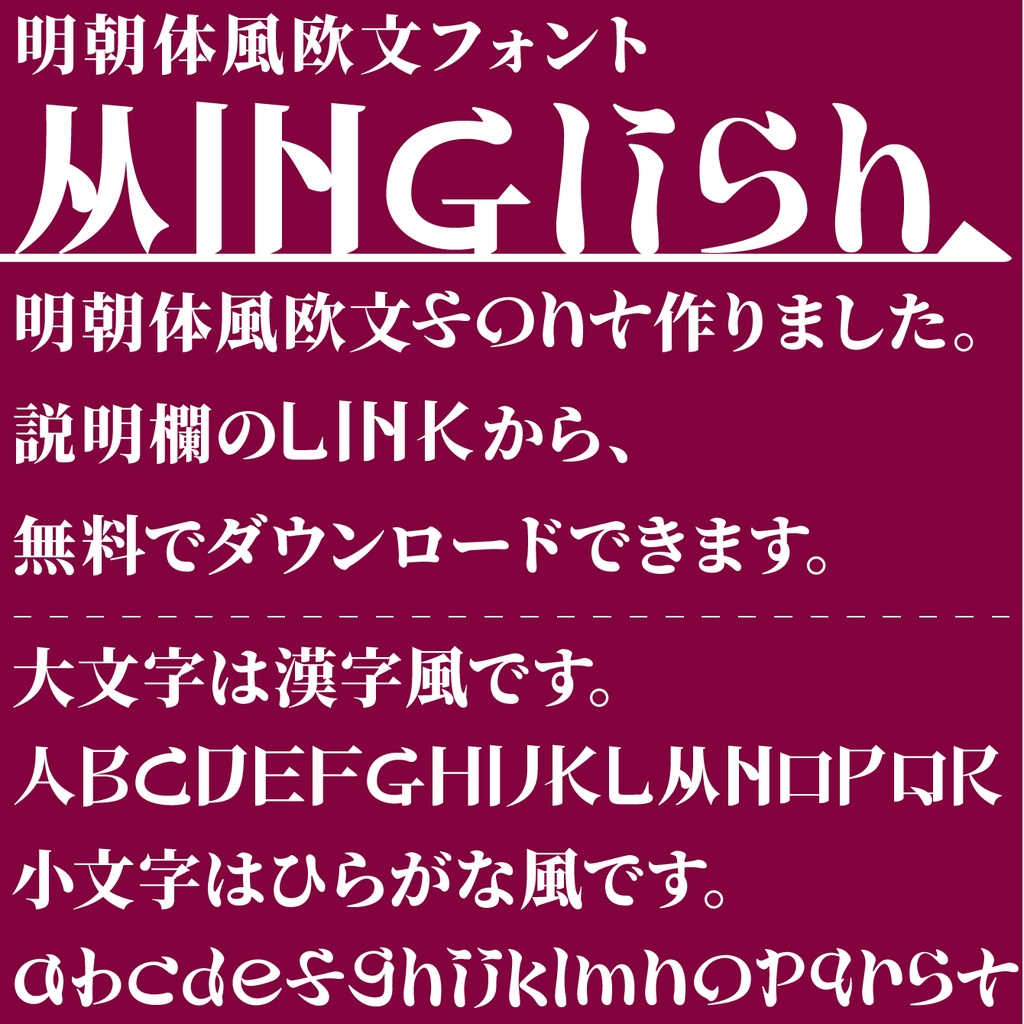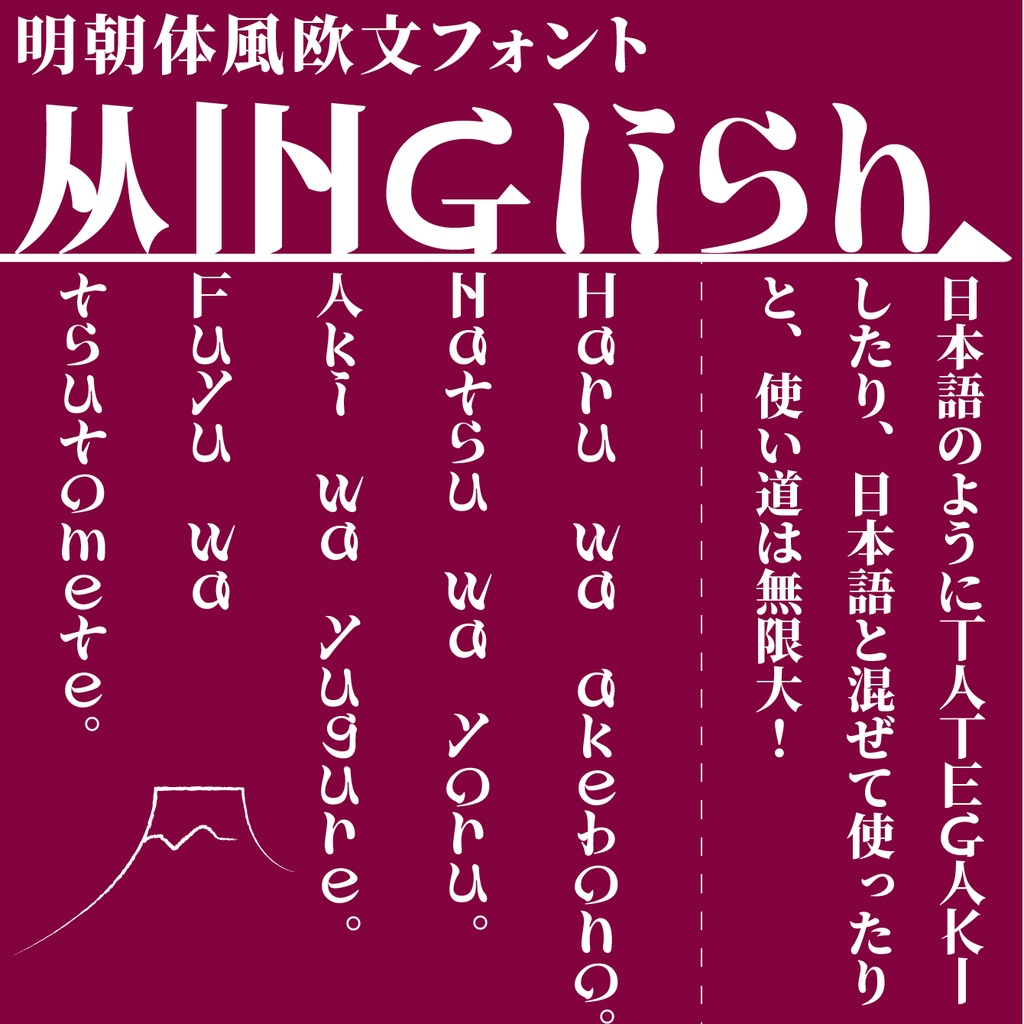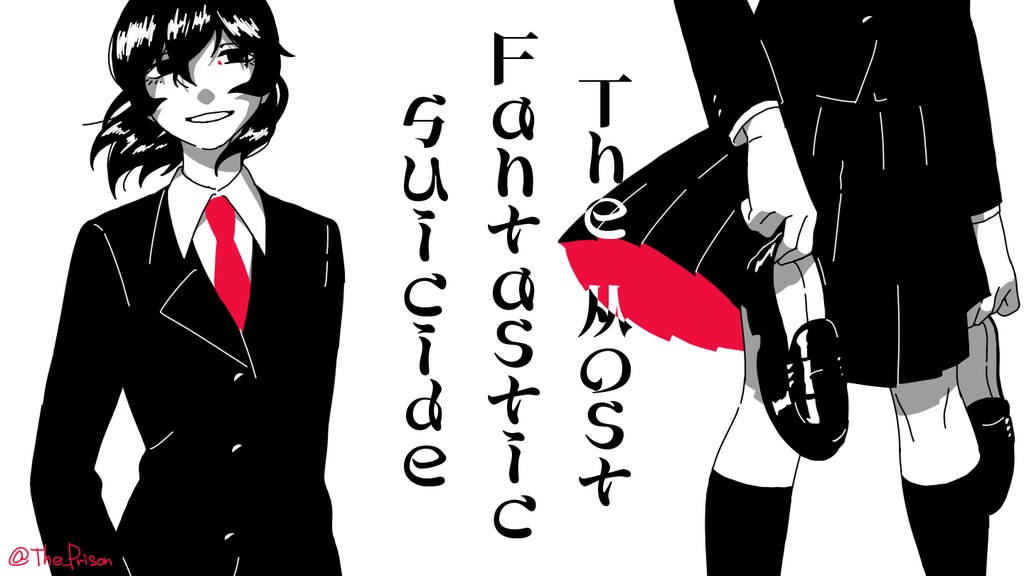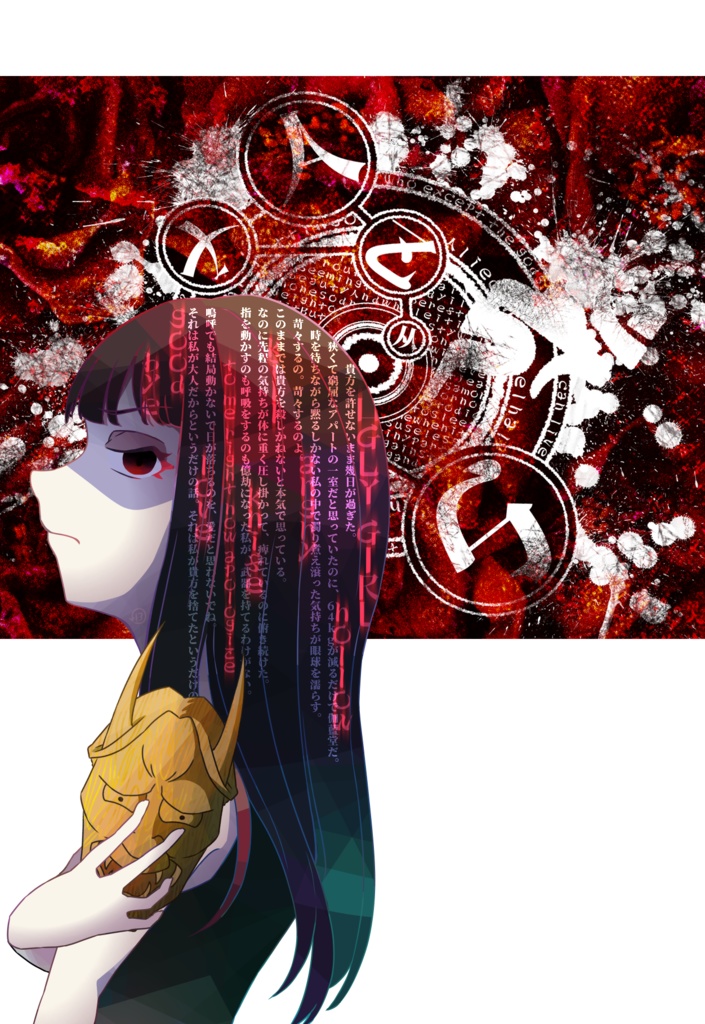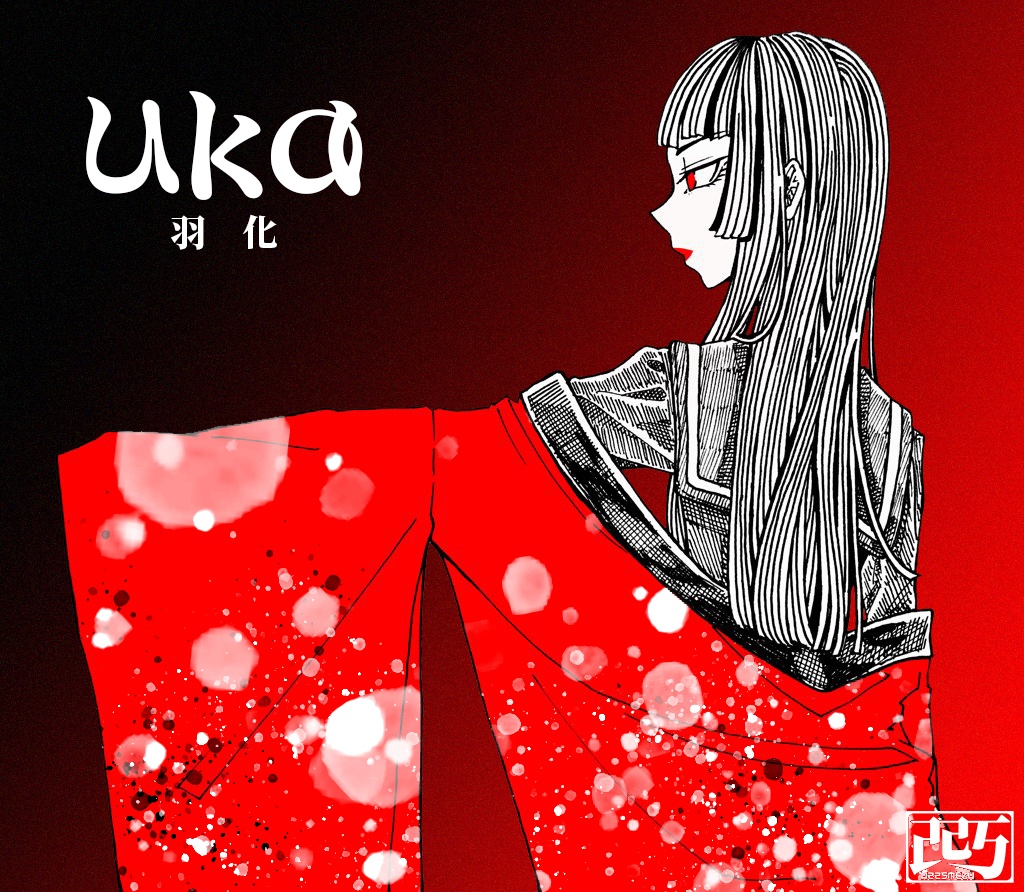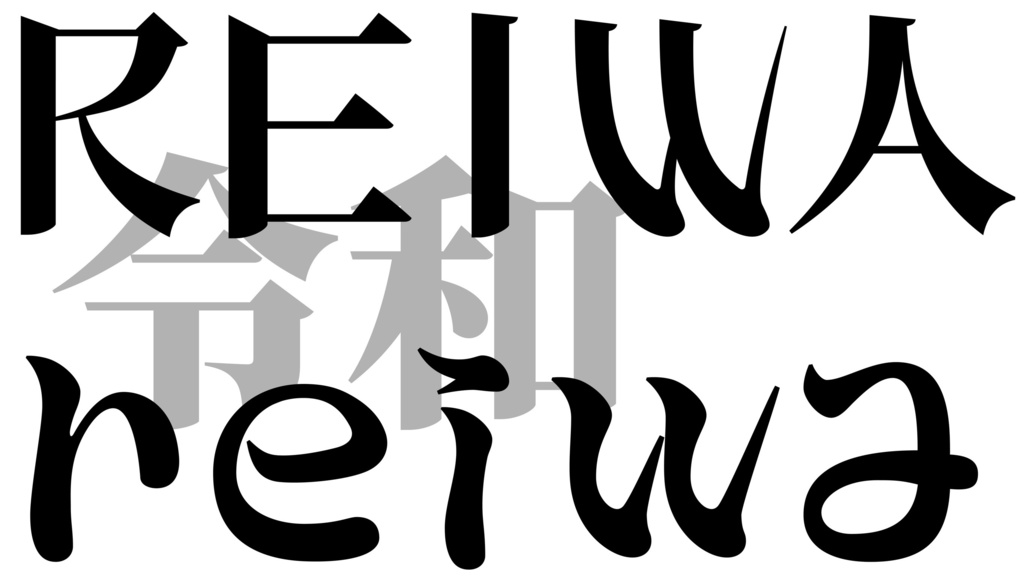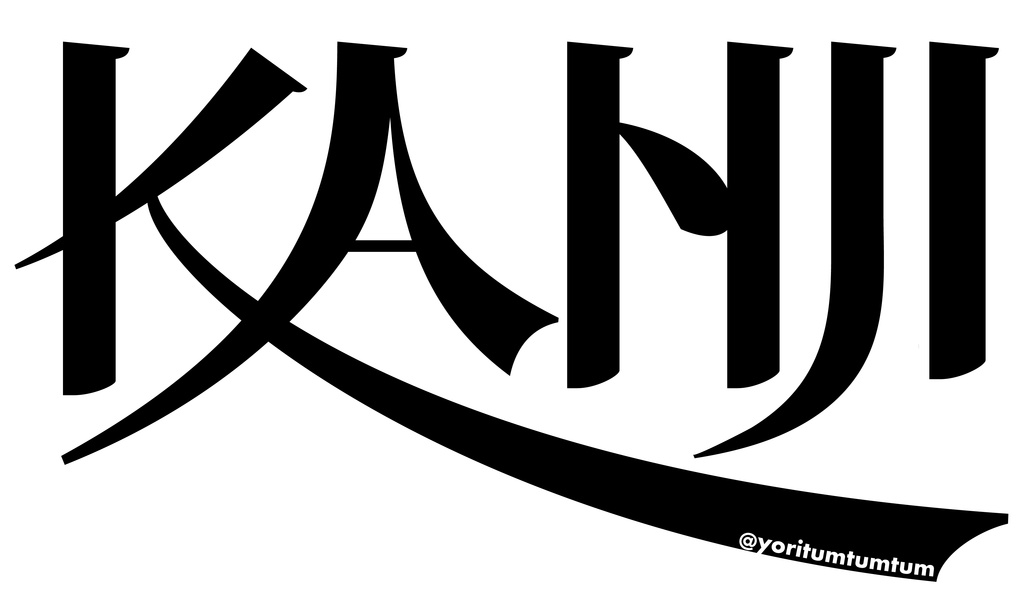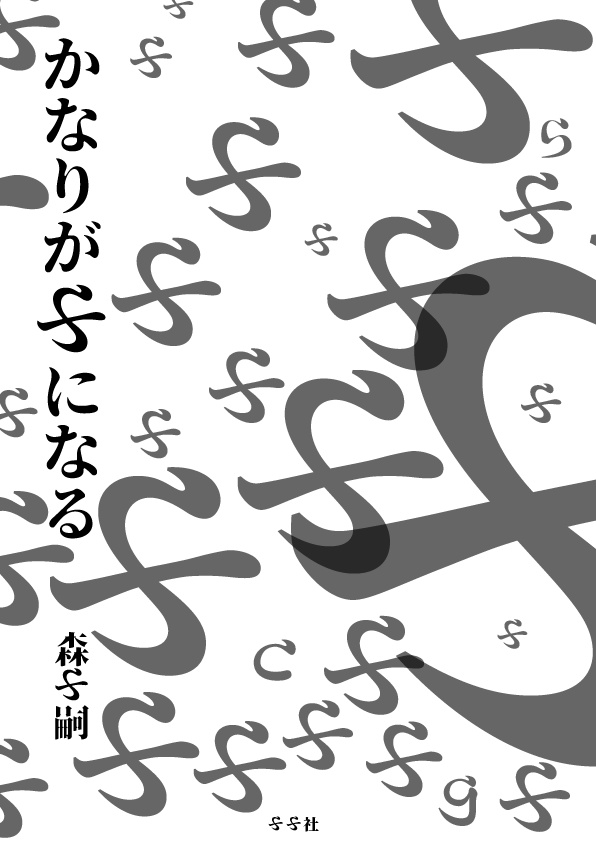
明朝体風欧文フォントMinglish
大文字が明朝体の漢字モチーフ、小文字は明朝体のひらがなモチーフなのが特徴の明朝体風欧文フォントです。 無料版と投げ銭版に違いはありません。 気に入りましたら、投げ銭でフォント製作を支援していただけると嬉しいです。 詳細はこちらから https://note.mu/yoritumtumtum/n/n0e76dc003ce3 フォントについて 制作した文字は、アルファベット大文字26字・小文字26字の合計52字です。 制作した文字は、半角英字と全角英字に収録されています。どちらも同じ形をしています。 Minglishは、記号、漢字、ひらがな、カタカナを補填するため、「源ノ明朝Heavy」との合成フォントになっています。 そもそもMinglishは「源ノ明朝Heavy」の漢字・ひらがなを参考に作っていますので、「源ノ明朝Heavy」と合わせやすくなっています。 是非日本語と混ぜて使ってください。 ライセンスについて Minglishは、参考元・合成フォント元である源ノ明朝と同様に、"SIL Open Font License 1.1"に従います。 大まかに言えば、 ・商用使用や改変、埋め込みをすることができる ・このフォントによる損害等に対する責任は一切負わない と言う内容です。詳しくはリンクをご覧ください。 https://ja.osdn.net/projects/opensource/wiki/SIL_Open_Font_License_1.1 以上の仕様を了解した後、この下からダウンロードください。